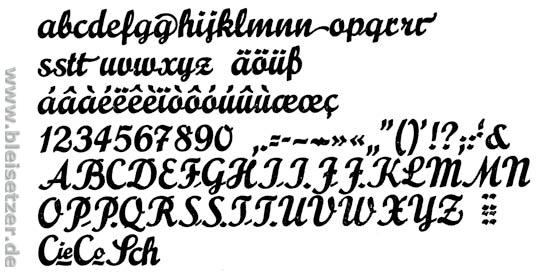
Schrift: der kleine Prinz
welche Schriftart könnte das sein?
Es gibt sicher viele digitalisierte Schreibschriften mit ähnlich gewollt-naivem Charakter. Das hier z.B. ist die Schrift "Prägefest" (sie heißt so, weil man damit - im Gegensatz zu anderen Schreibschriften mit überhängenden Ober- und Unterlängen) hervorragend prägen kann:
Gruppe VIII - Schreibschriften - Prägefest
Ludwig & Mayer, Frankfurt am Main
Erstguß 1926
Eduard Lautenbach
Ich meine, jemand hätte auch einmal erwähnt, daß es diese Schrift als digitalisierten Font gibt.